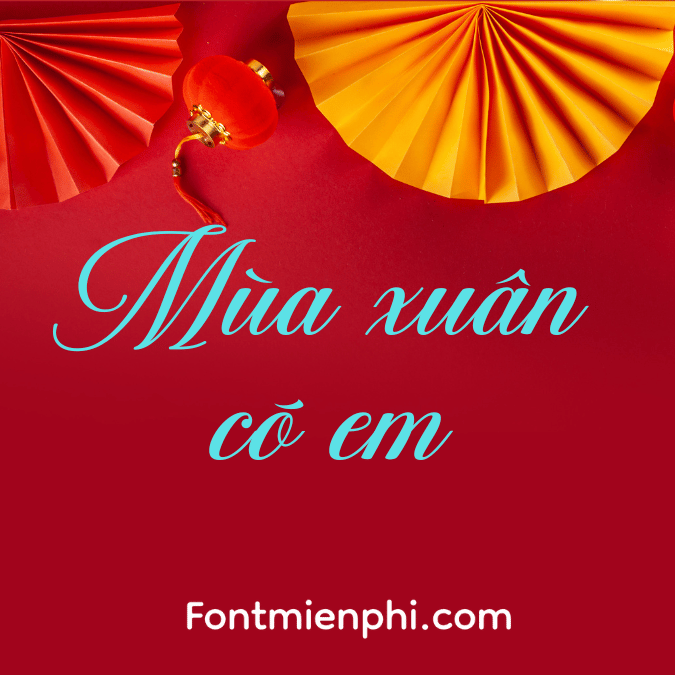
Font Việt hóa 1FTV VIP Peristiwa ,Font tết
Font Việt hóa 1FTV VIP Peristiwa
Font Việt hóa 1FTV VIP Peristiwa là một kiểu chữ được thiết kế đặc biệt để hỗ trợ việc viết tiếng Việt. Font này có những đặc điểm nổi bật như sau:
1. Thiết kế hiện đại: Font này mang phong cách hiện đại, dễ đọc và phù hợp với nhiều mục đích sử dụng, từ đồ họa, truyền thông đến in ấn.
2. Hỗ trợ đầy đủ ký tự tiếng Việt: 1FTV VIP Peristiwa cung cấp đầy đủ các ký tự tiếng Việt, bao gồm cả các dấu như hỏi, ngã, sắc, huyền, và nặng, giúp người dùng có thể viết chính xác và tự nhiên.
3. Độ nét cao: Font này có độ nét cao, giúp các văn bản trông rõ ràng hơn trên cả màn hình và giấy in.
4. Tính linh hoạt: Có thể sử dụng trong nhiều ứng dụng khác nhau như thiết kế đồ họa, trình bày slide, hoặc tạo nội dung web.
5. Phong cách độc đáo: Với thiết kế riêng biệt, font này tạo nên sự khác biệt cho các sản phẩm thiết kế, làm nổi bật nội dung và thu hút người đọc.
Font Việt hóa 1FTV VIP Peristiwa là sự lựa chọn lý tưởng cho những ai muốn sử dụng một kiểu chữ vừa đẹp mắt vừa dễ dàng trong việc thể hiện ngôn ngữ tiếng Việt.